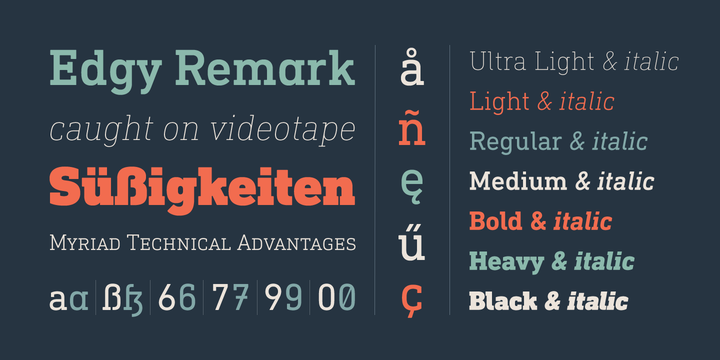
Welche (Serifen)-Headline-Schrift passt zu der DIN?
Naja, ob die Baskerville nun langweiliger ist als die Caslon oder DIN, darüber ließe sich sicher streiten. Im Kontext zur DIN finde ich sie spannend gesetzt, formal passender.  :roll:
Aber gut – ich werfe mal noch die Walbaum in die Runde ;-) (könnte man auch schön mit der Walbaum Grotesk kombinieren).
Und sollte man es doch etwas humanistisch-verspielter mögen, könnte auch ein Blick bei Goudy lohnen. (Aber ob die Renaissance-Formen für dieses Thema und die gewählte Textschrift nun meine erste Wahl wären, weiß ich nicht.)
Walbaum wollte ich auch schon fast vorschlagen  :gimmifive:
Die Caslon ist ja schon eigenwilliger und verspielter als die Baskerville, weswegen ich für längere Texte die zweite vorziehen würde, hier aber eben nicht.
Könnte sogar mit auf die noch offene Liste »Empfehlenswerte Versaleszett-Formen in Egyptienneschriften«.  :nicken: Bei dieser Spezies scheinen gute Beispiele ja eher noch die Seltenheit zu sein …
hübsch! und schön das die italic ein alternatives a hat. ich wollte dieses jahr eigentlich keine fonts mehr kaufen. ach, egal! :ilovetype:
ich frage mich eh, wieso albert noch keine din slab für FF entworfen hat. nun war linotype schneller, aber ist ja mittlerweile eh alles ein club ;)
Hallo ich suche für den Bereich Architektur eine Schrift für den Fleisstext, als Headline Schrift würde ich gern die DIN Next Pro nehmen.
Was könnte eurer Meinung nach gut passen?
Außer einer weiteren Serifenlosen passt so ziemlich alles. Am wenigsten falsch kann man wahrscheinlich mit einer Renaissance-Antiqua machen.
Und welche auf den Mac verfügbaren kostenlose könnte man einsetzen?